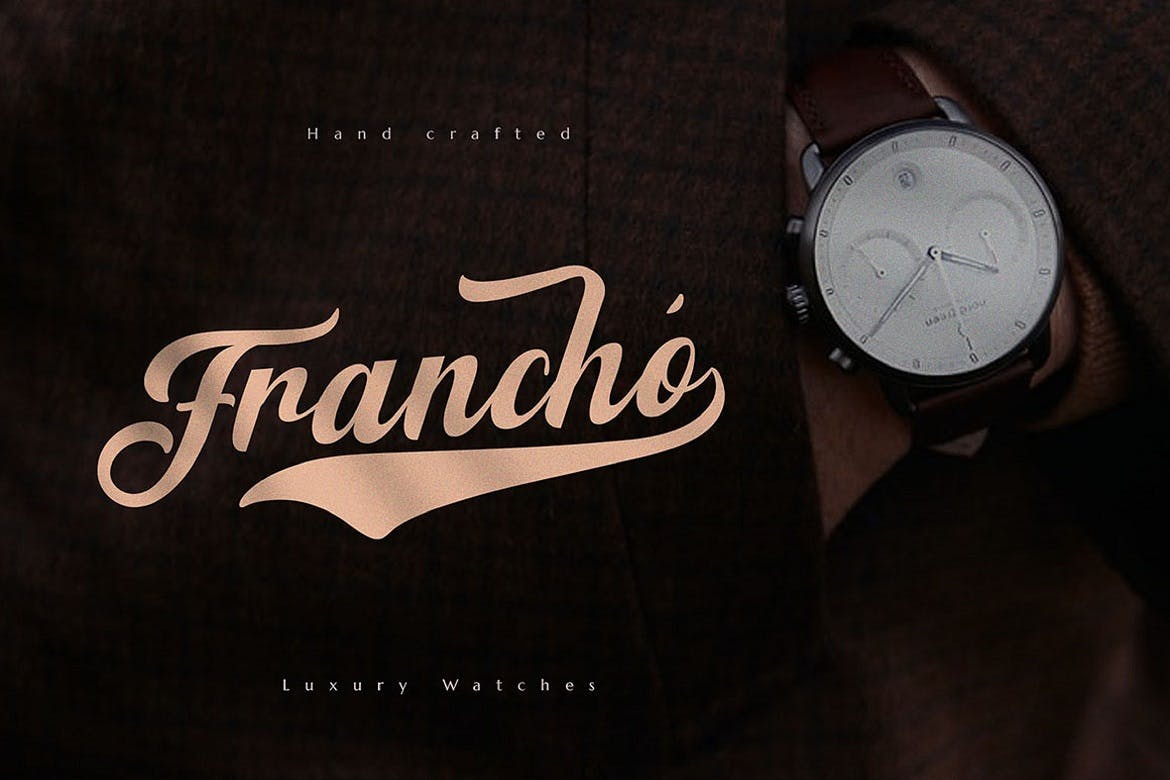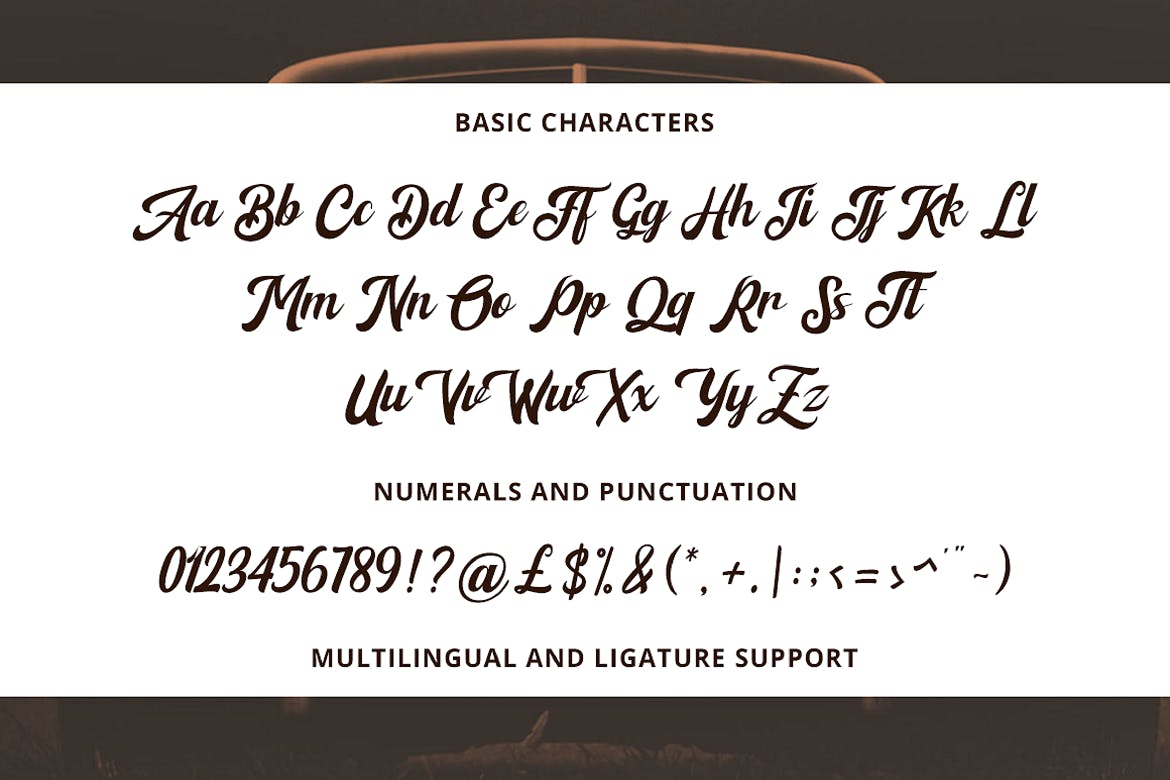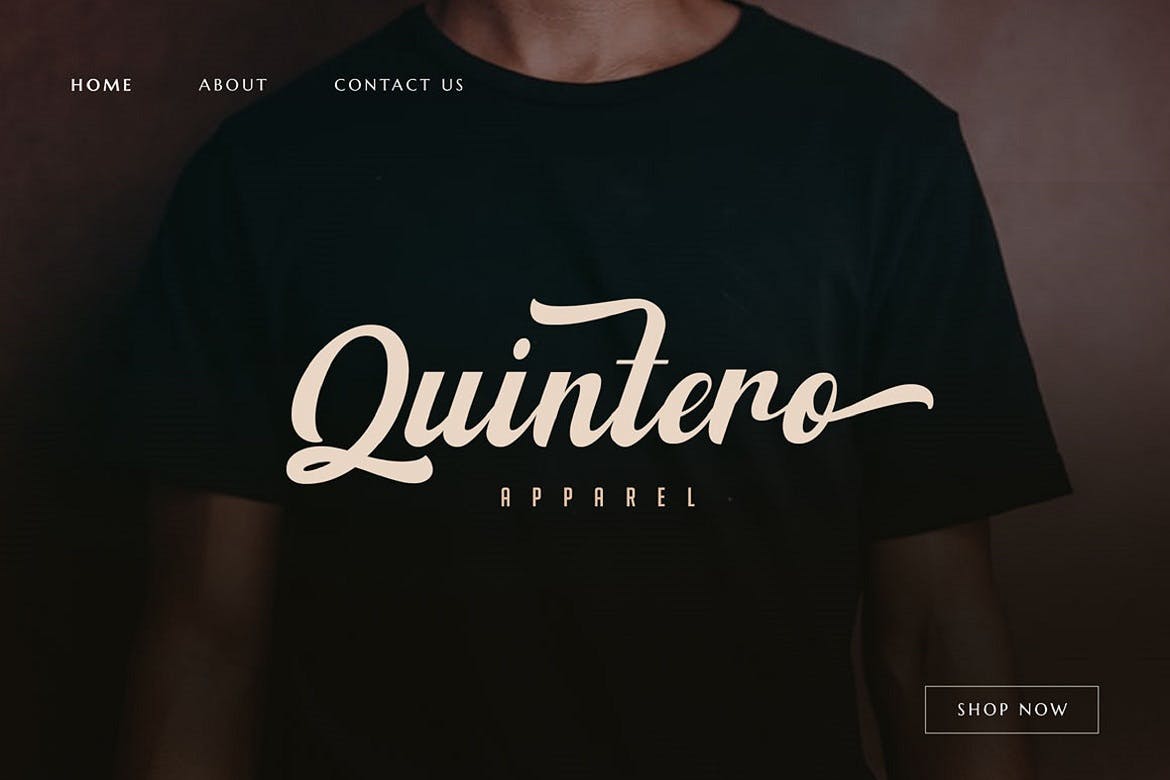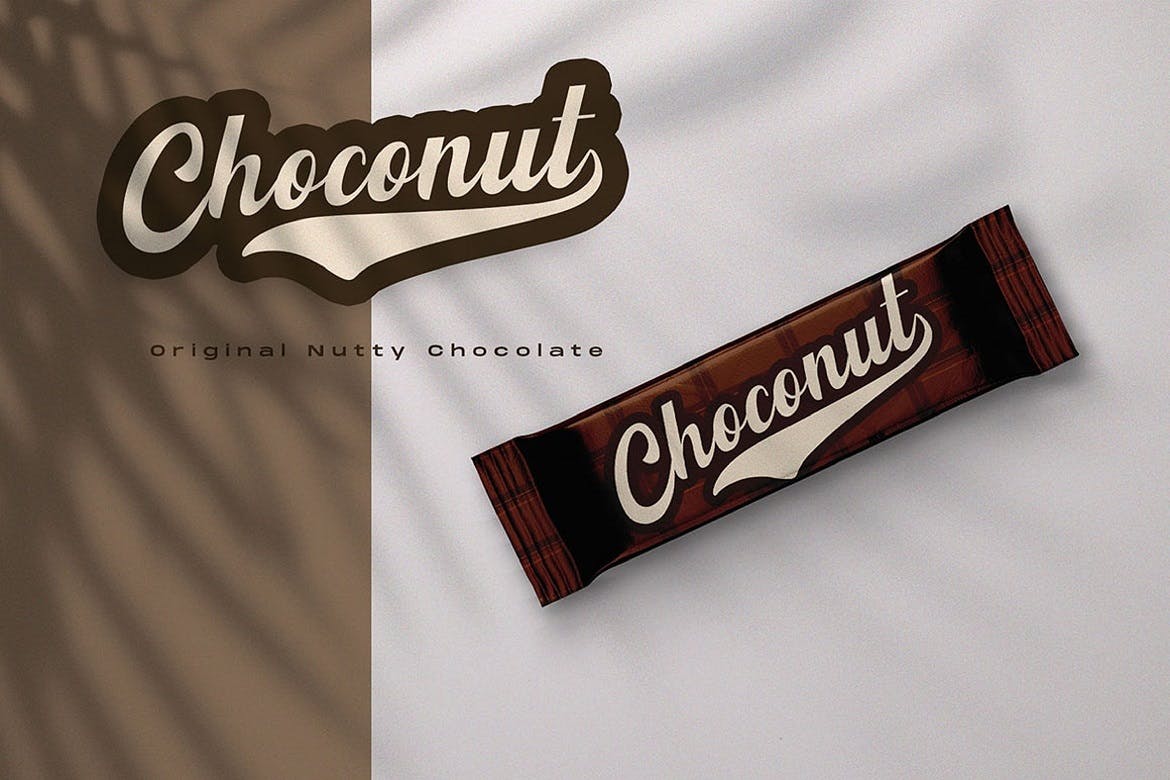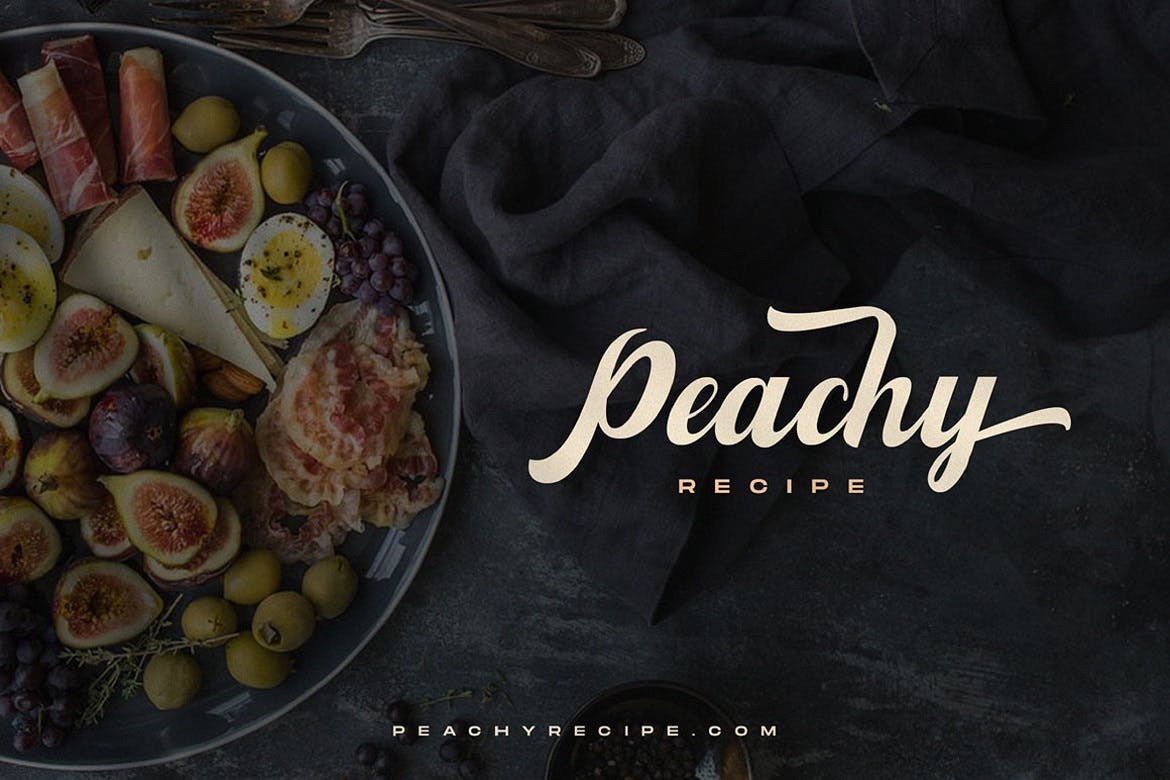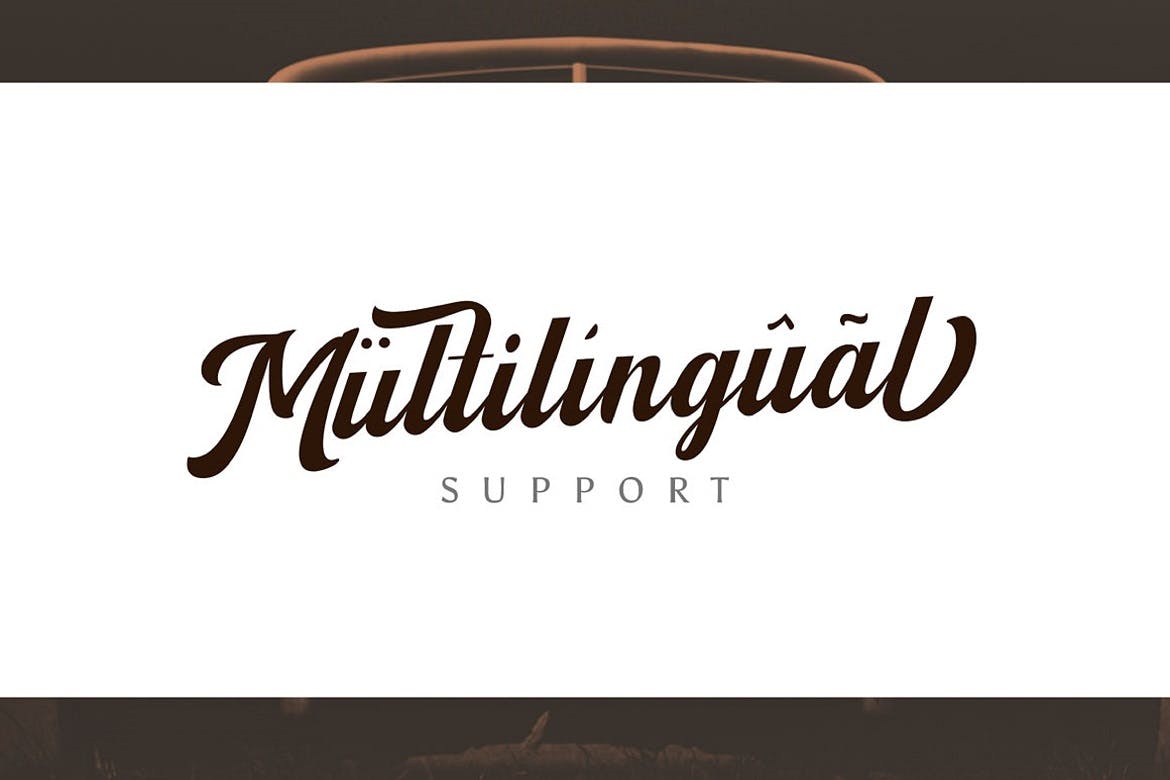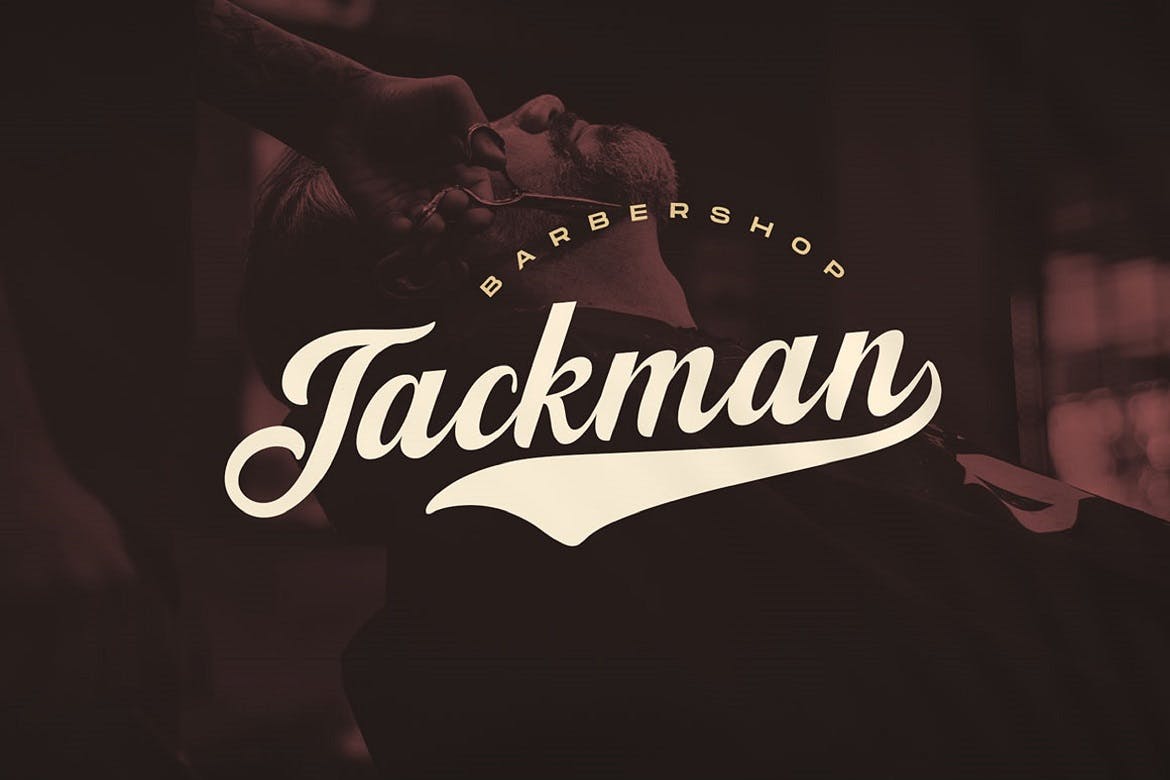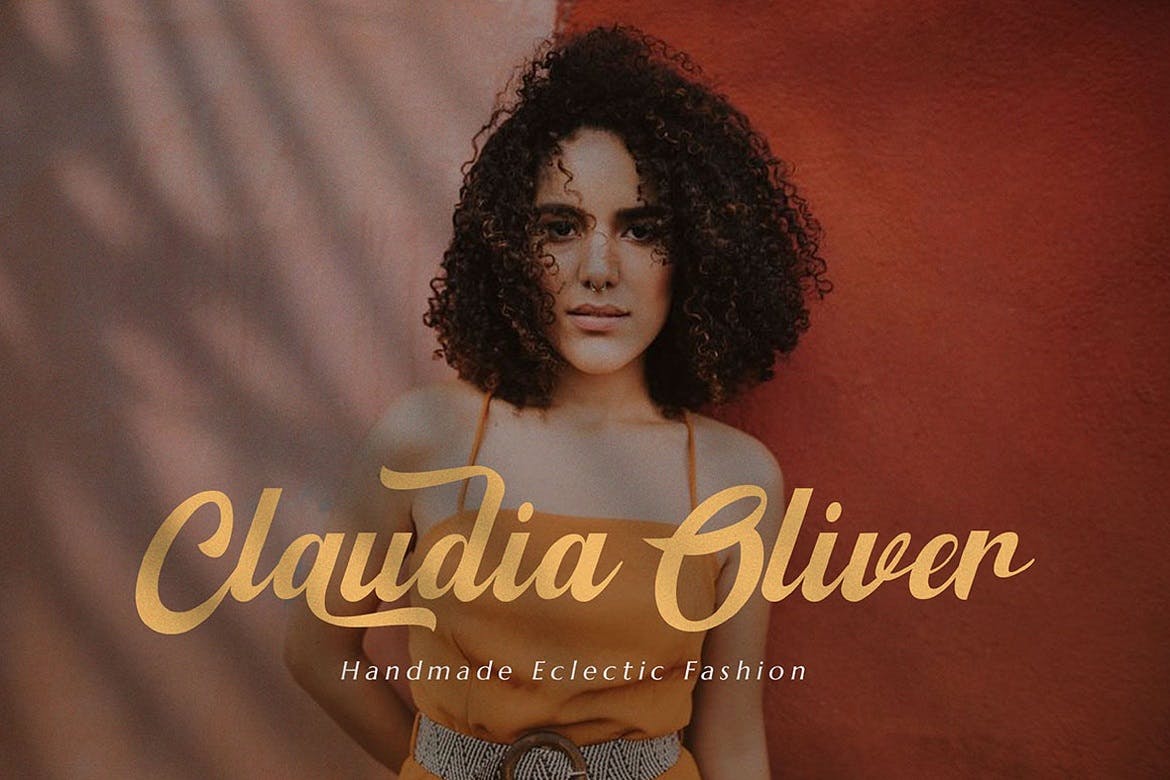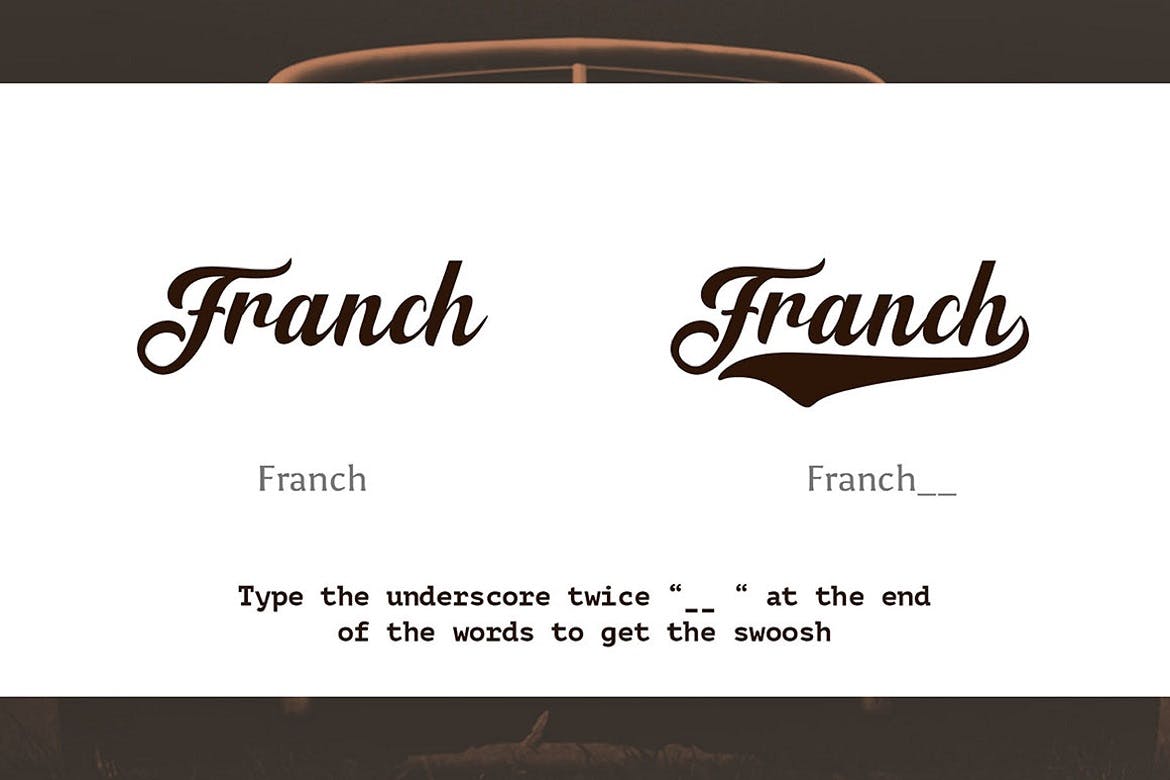
فونت Fenway
آیا آمادهاید تا به عمقهای غنی تاریخ نفوذ کنید؟ آیا میخواهید برندینگ خود را جذاب کنید؟ آیا به دنبال یک فونت خاص هستید که برجستگی، سبک و ماجراجویی را به نمایش بگذارد؟
معرفی میکنیم: Fenway - یک فونت اسکریپت تمیز.
این فونت اسکریپت تمیز برای انواع مختلف نیازهای محتوا و پروژهها قابل استفاده است. از آن برای برجسته کردن عناوین خود، بهبود لوگوها، طراحی کارتهای ویزیت، ارتقاء وبسایت و شبکههای اجتماعی خود و ایجاد کلاس، سبک و تاریخ در تمامی کانالهای خود استفاده کنید.
آماده باشید تا مخاطبان و مشتریان خود را با فونت Fenway جذب، درگیر و الهامبخش کنید.